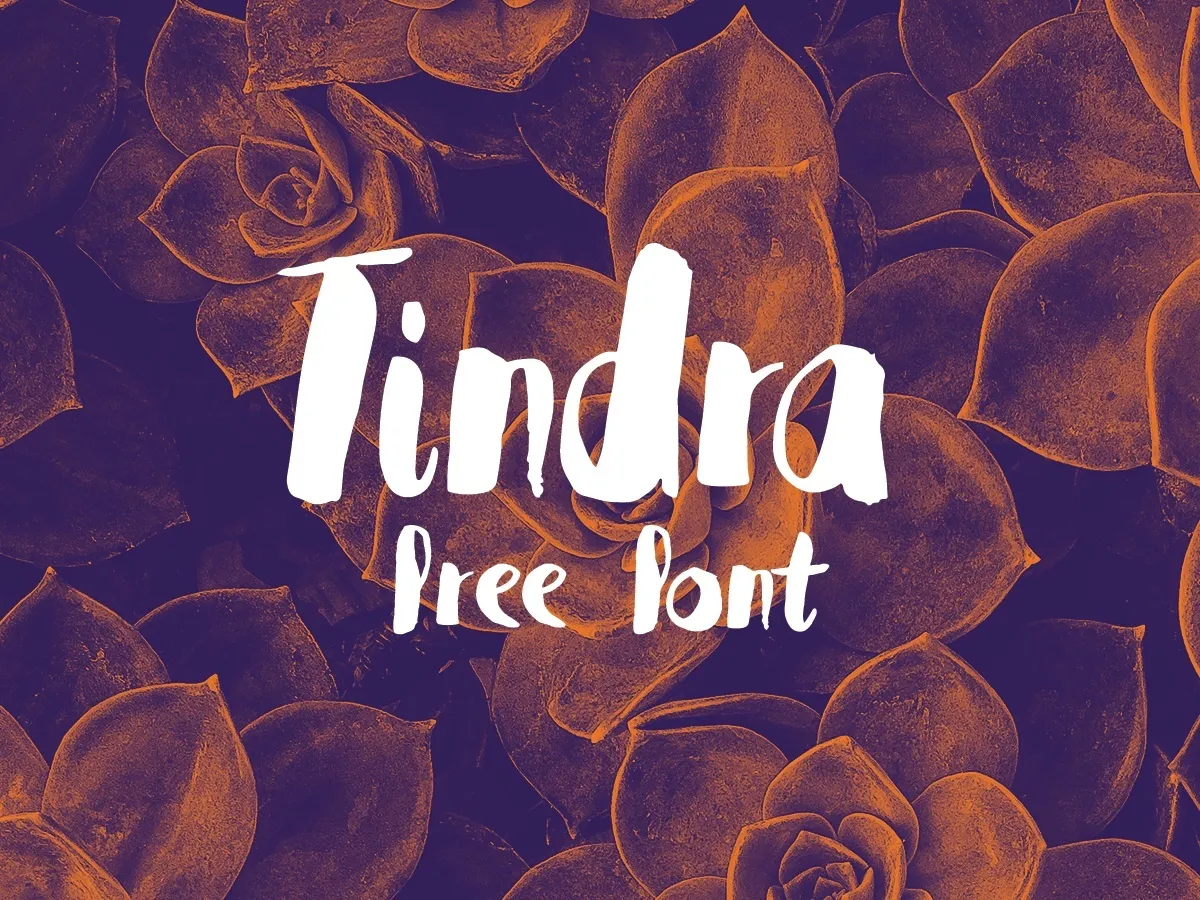
Tindra Font – Download Grátis
Aqui está uma descrição envolvente para a página de download da fonte ‘Tindra Font’ em português brasileiro: A fonte Tindra é perfeita para quem procura um estilo elegante e sofisticado que combina elementos artísticos com uma leveza moderna. Com traços finos e acabamentos delicados, ela se destaca como a escolha ideal para textos de destaque em sua próxima publicação ou design gráfico. A fonte Tindra foi criada pelo designer Hamilton, resultando num trabalho que vai além da simples tipografia. Ela transmite um sentimento único através dos seus traços fluidos e elegantes, capazes de destacar qualquer texto ao qual é aplicado. Suas linhas suaves e detalhes meticulosamente trabalhados fazem dela uma opção ideal para designers gráficos que buscam personalidade em suas criações. Ideal tanto para nomes comerciais como para textos interativos, a fonte Tindra oferece um toque único capaz de tornar qualquer projeto mais profissional e impecável. Ela é perfeita para títulos de página ou pequenos detalhes em letras finas sem comprometer o impacto visual do design. A fonte Tindra não só adicionará um toque sofisticado a seus projetos, mas também ajudará você a destacar seu trabalho no meio de uma vasta variedade de recursos gráficos disponíveis atualmente.